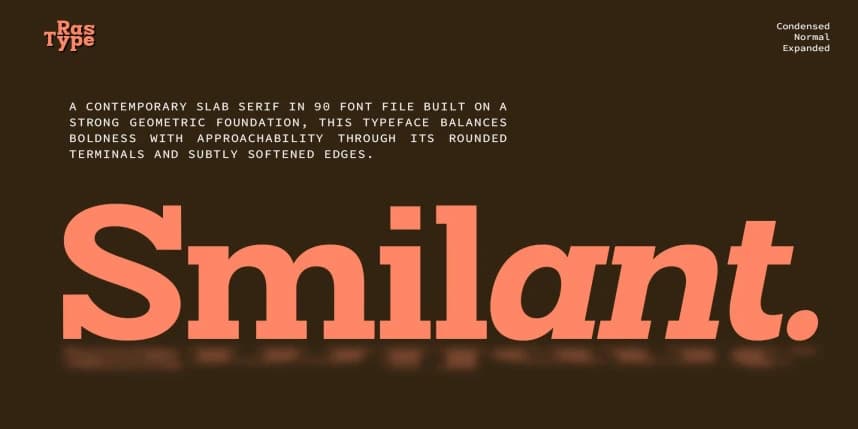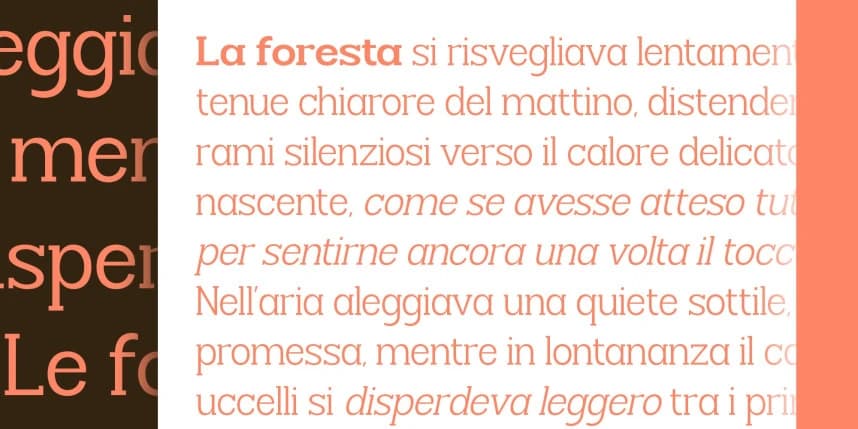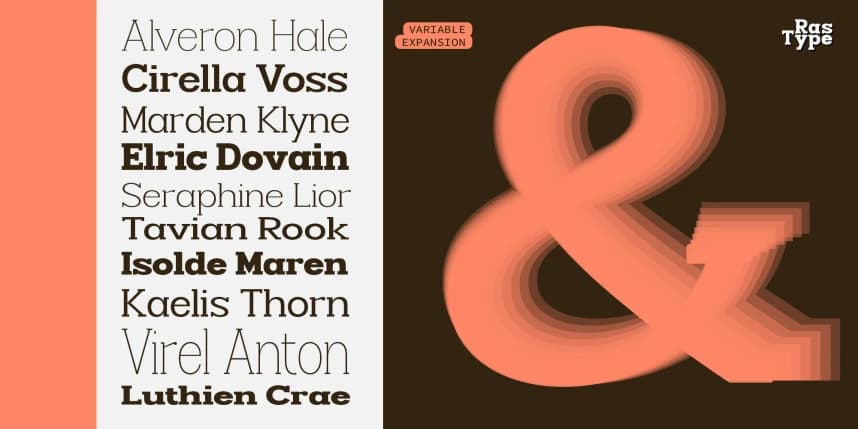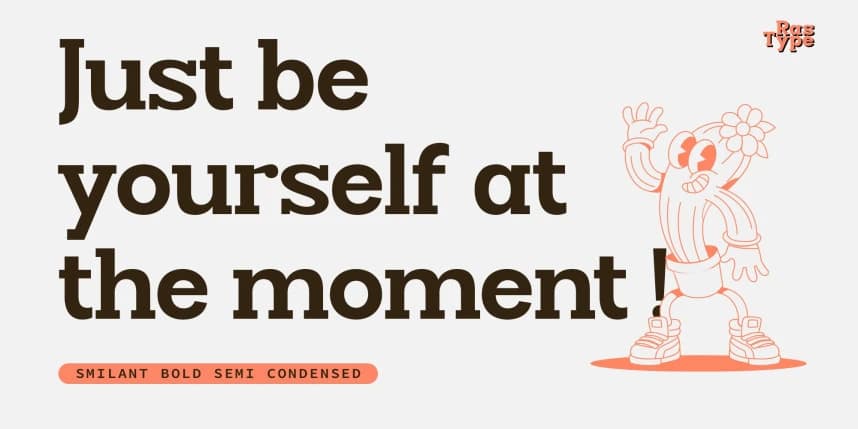
Smilant Font Family
Smilant Font Family - Bu yazı tipi, güçlü geometrik bir temele dayanılarak inşa edilmiş çağdaş bir slab serif'tir; cesur yapıyı sıcak ve ulaşılabilir bir hisle birleştirir. Belirgin, blok biçimli serifler istikrar ve güven sağlar.
Smilant Font Family - Bu tipografi, güçlü geometrik bir temele dayalı çağdaş bir slab serif olup, kalın yapıyı sıcak, yaklaşılabilir bir hisle birleştirir. Öne çıkan, blok görünümlü serifler istikrar ve güven sağlar